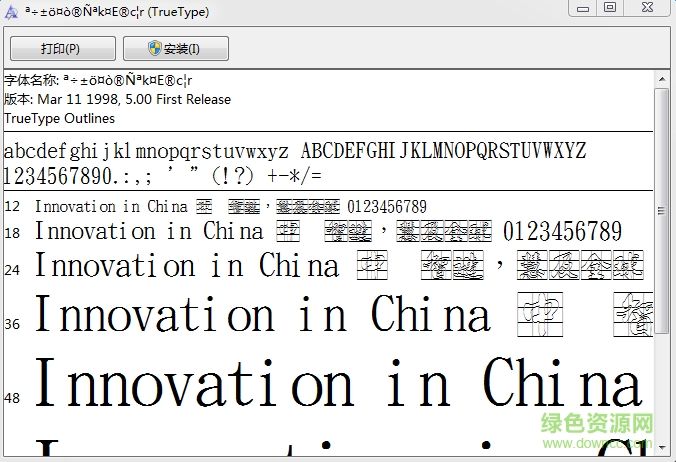
金梅毛書法九宮字體是由綠色資源網(wǎng)站為大家整理的免費字體文件。這個字體風(fēng)格很獨特,所有字體都被九宮格保衛(wèi)者,設(shè)計一些醒目突出的標題很合適!需要的用戶快來綠色資源網(wǎng)下載吧。
金梅毛書法九宮字字體是一種很有特色的書法字體,該字體寫出來的字不像其他字體那樣古板,很活潑、很好看,適合書法題字、寫詩等!